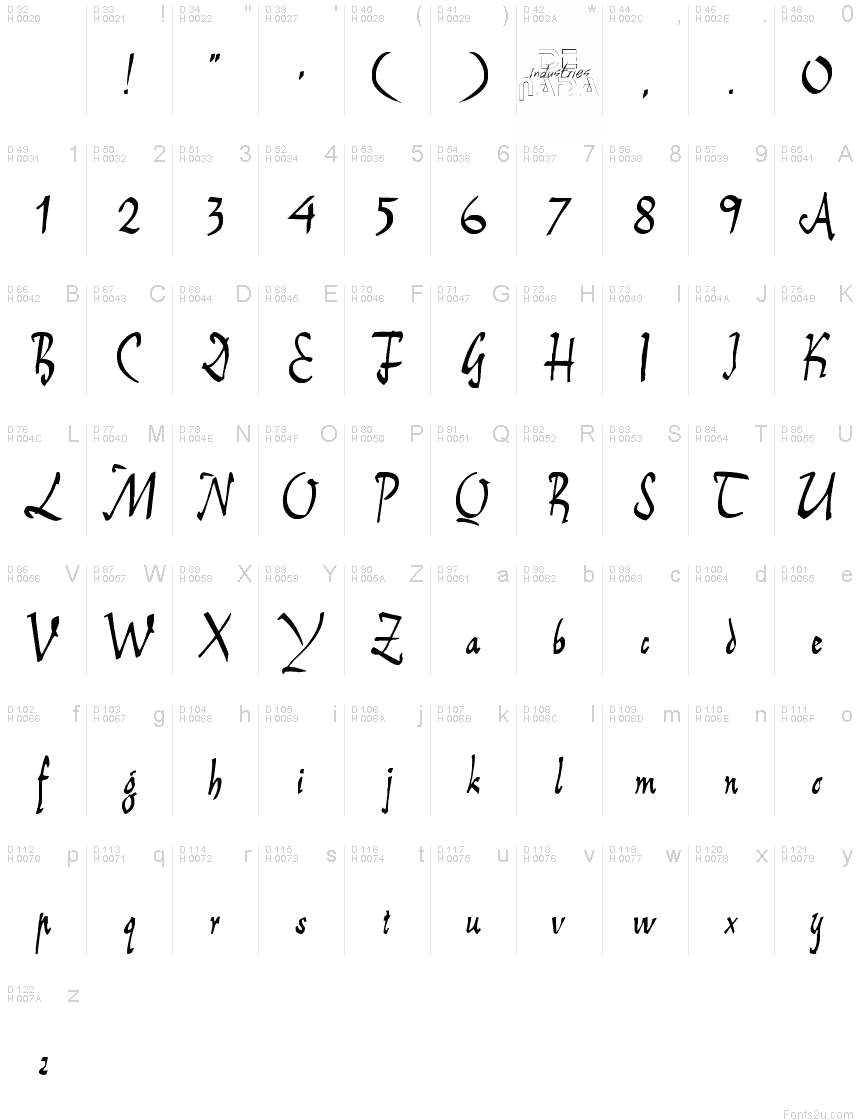
E-BrantScript od De Nada Industries to darmowy, odręczny krój pisma. Ten font z rodziny E ma charakterystyczny wygląd suchego pędzla i lekko poszarpanego tuszu, co nadaje mu ciepła, unikając przy tym przesłodzonego efektu. Pociągnięcia są zamaszyste i pewne, a luźne światło między literami sprawia wrażenie szybkiego podpisu na fakturowanym papierze.
E-BrantScript świetnie sprawdza się w logotypach, opakowaniach butikowych, menu kawiarni, kartkach okolicznościowych, okładkach albumów, grafikach z cytatami oraz nagłówkach w mediach społecznościowych, gdzie chcesz wprowadzić odrobinę ludzkiej energii. Wypróbuj go w większym rozmiarze (jako nagłówki), aby detale pędzla pozostały wyraźne, i zestaw ten darmowy font z czystym, geometrycznym bezszeryfowym krojem dla kontrastu.